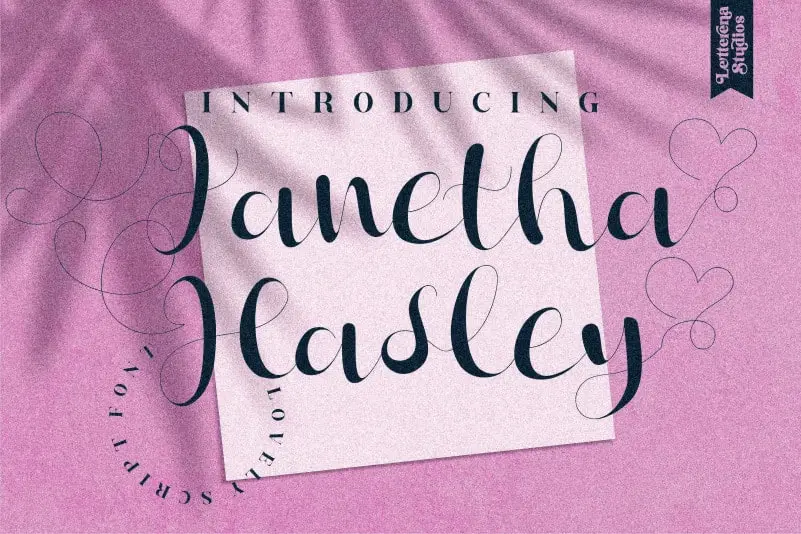
Janetha Hasley Script Font – Download Grátis
A fonte Janetha Hasley Script é uma seleção perfeita para quem busca uma mistura romântica e delicada do estilo de escrita. Com seus caracteres que dançam sobre a linha base, esta fonte atinge um patamar especial no universo dos tipos de escrita, combinando sofisticação com uma graça encantadora. Ideal para diversas aplicações como logotipos, convites de casamento, subtítulos e cabeçalhos, etiquetas, cartazes e até mesmo materiais promocionais como fitas de saudação ou badges. A sua característica mais brilhante é a PUA Encoded. Isso significa que você pode acessar todas as glifos e swashes sem qualquer dificuldade. Estes elementos especiais permitem uma maior liberdade criativa, permitindo-lhe explorar e moldar o design da fonte de inúmeras maneiras únicas. Janetha Hasley Script não só é perfeita para uso no seu próximo projeto gráfico, mas também pode transformá-lo em algo especial. Desde as letras digitais até os materiais impressos finos, esta fonte encanta e se adapta ao seu design de qualquer forma que você desejar. Descubra a magia da escrita artesanal com Janetha Hasley Script Font.